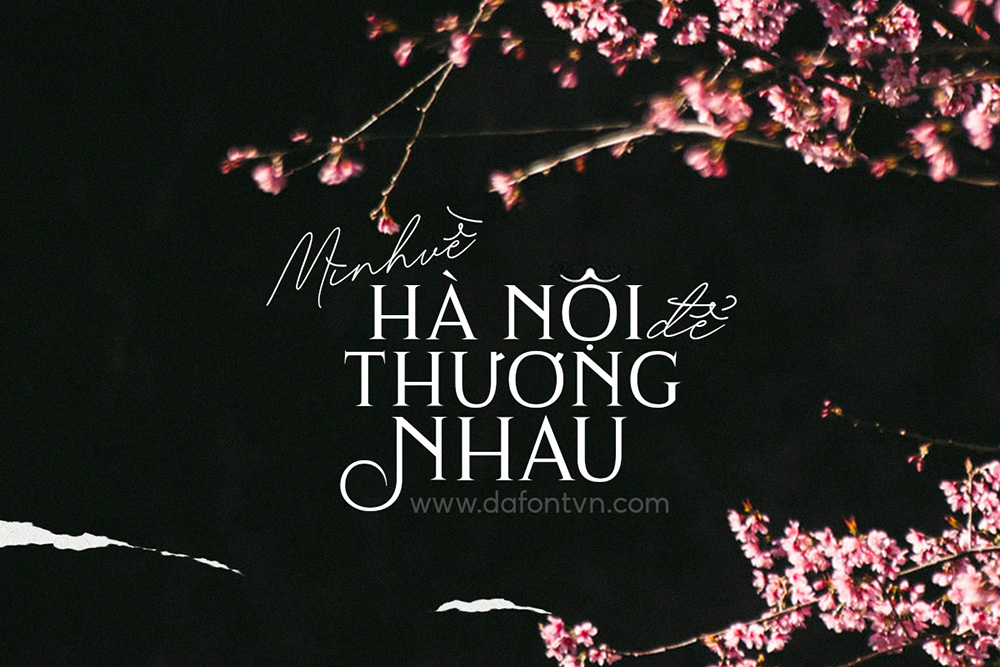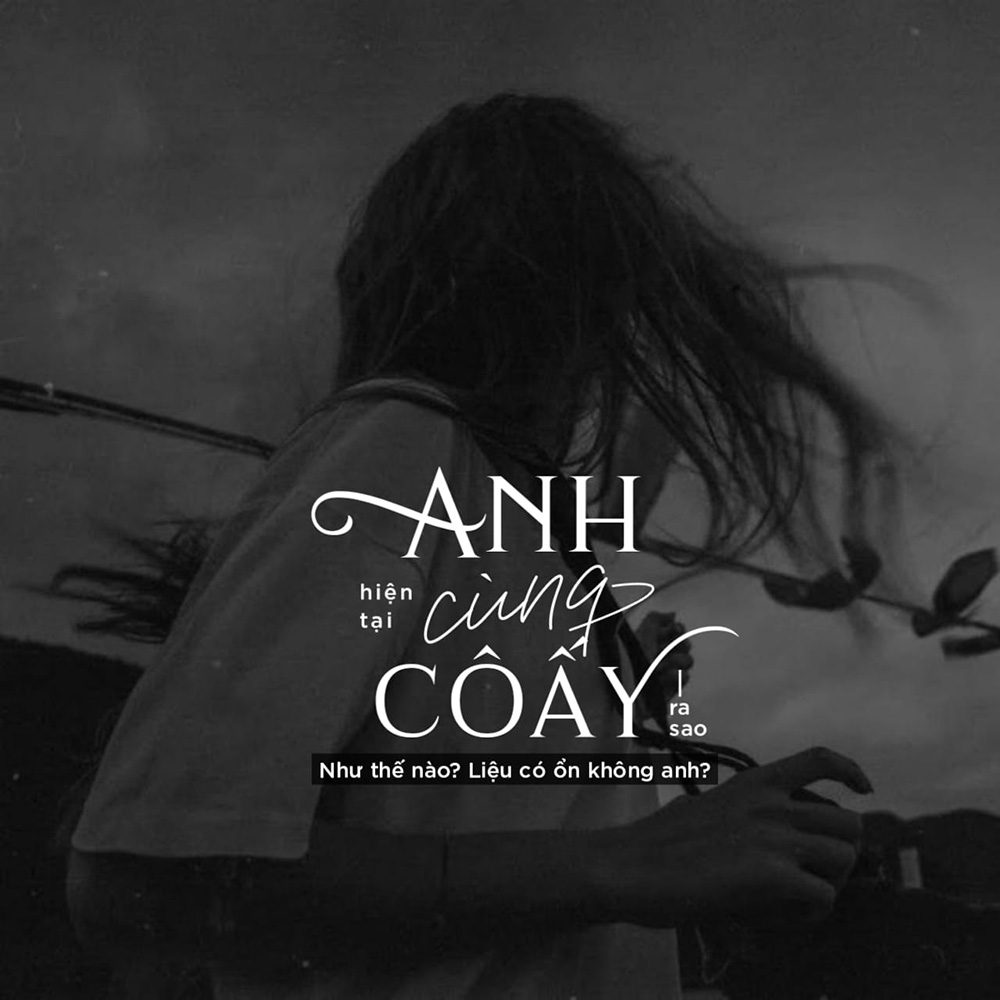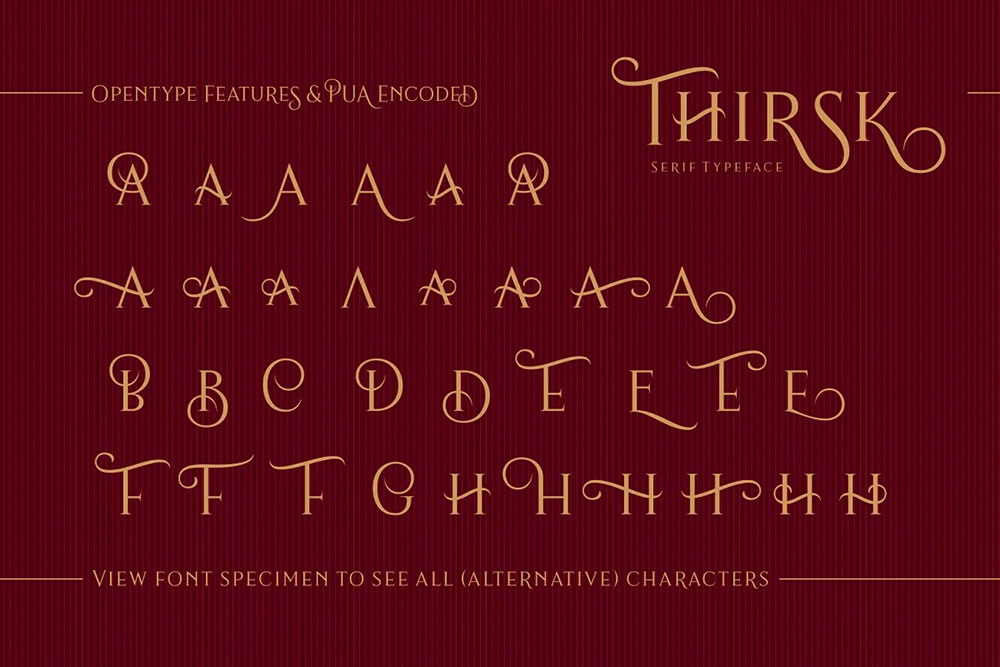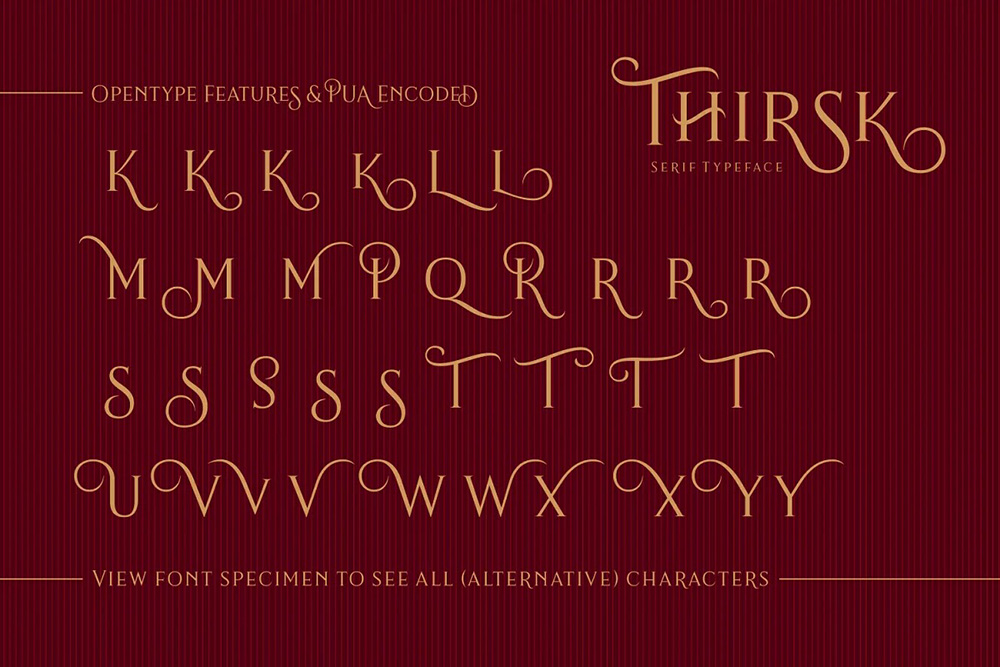
Font Việt Hóa - Thirsk Cực Đẹp Mang Phong Cách Đơn Giản, Hiện Đại
Font việt hóa Thirsk được thiết kế ấn tượng với rất nhiều glyhp đi kèm làm cho nó trở nên rất linh hoạt có thể được sử dụng trong nhiều dự án khác nhau. Một font chữ tưởng chừng đơn giản nhưng lại rất hiện đại bạn chắc chắn sẽ ấn tượng đấy hãy thử design xem nhé.